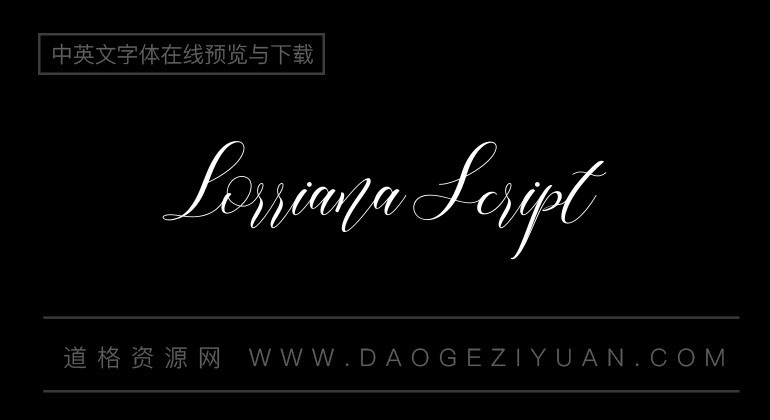
? Lorriana Script 是一款精致的手写字体,它的特点是每个字母都有温柔的曲线,字体非常适合用于拼写名字、标题、贺卡等等。它的外观柔和,却又充满活力,可以给你的设计增添一丝活力,给视觉效果增添一丝温柔。内容介绍
Lorriana Script是一款非常不错的手写艺术字体,具有很好的视觉感,适合于文化类的宣传设计、商业类品牌的广告和产品包装设计以及个性化文字排版等较多场景。